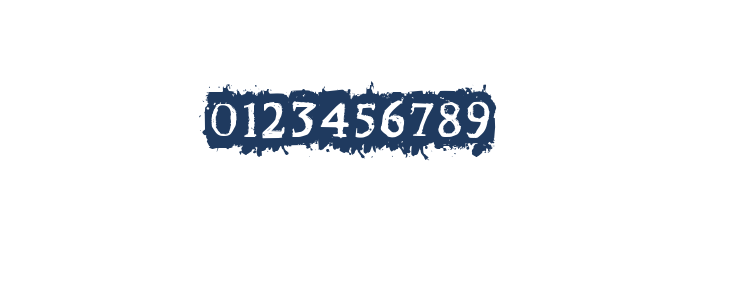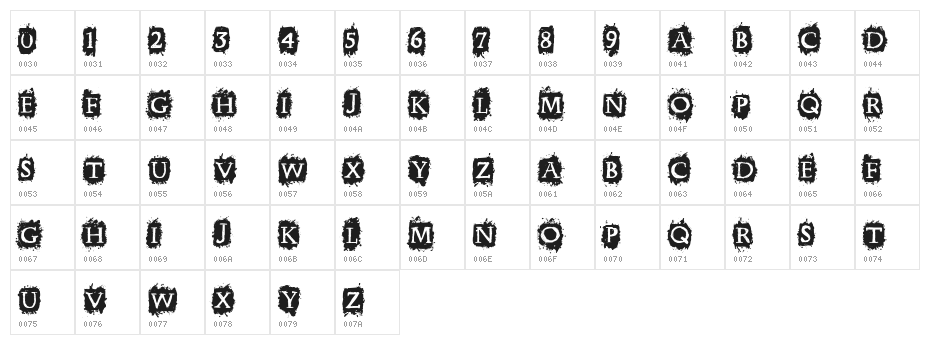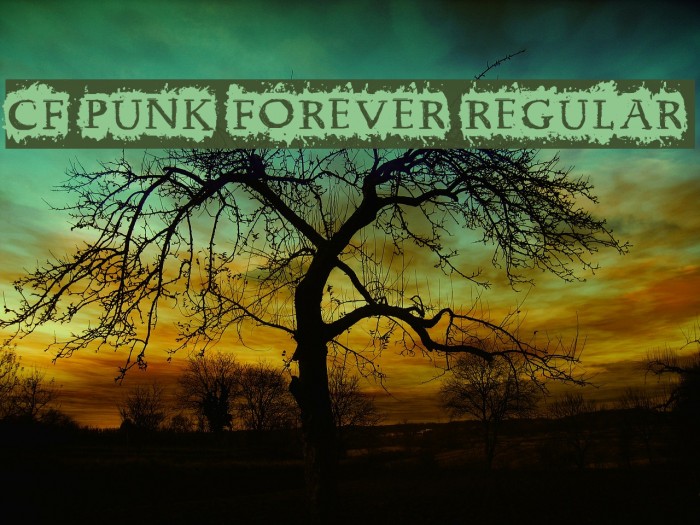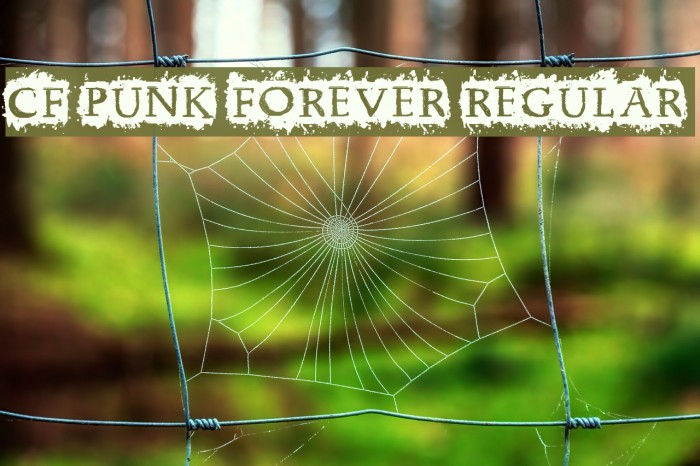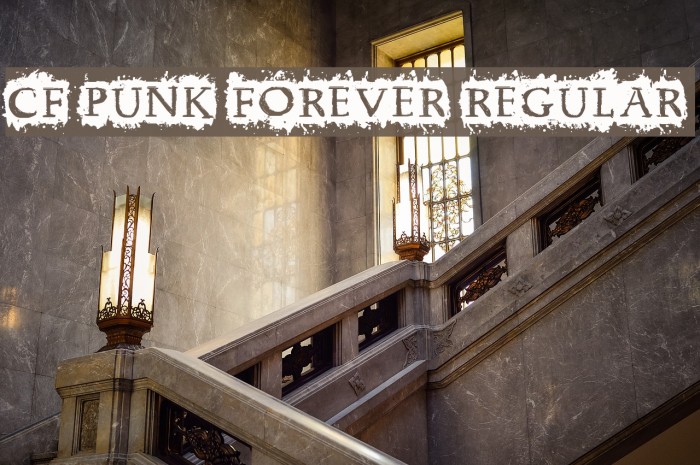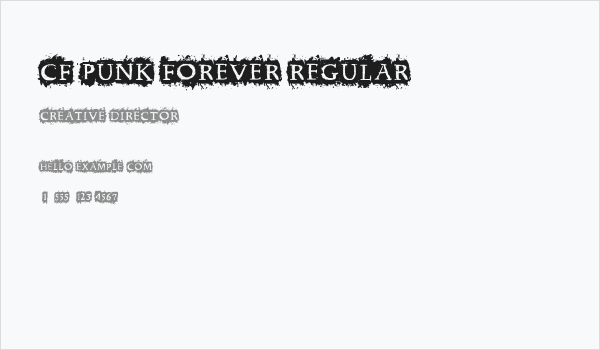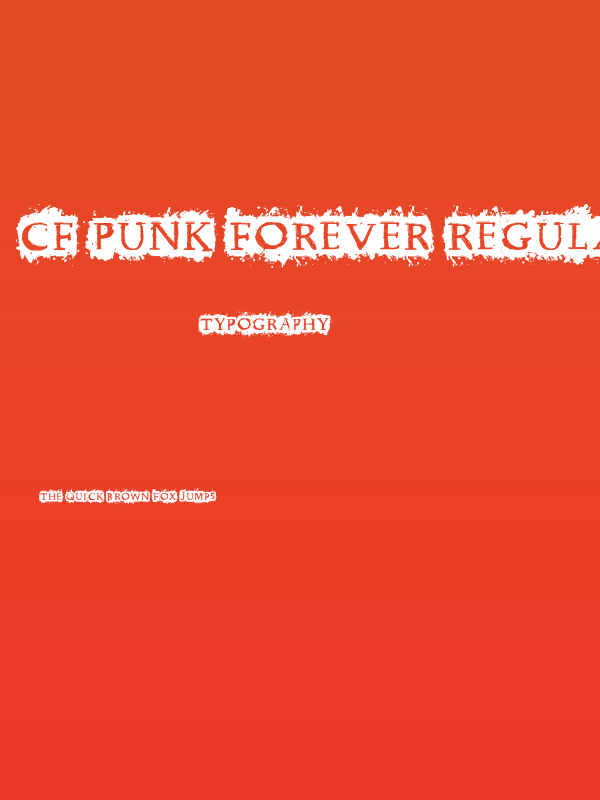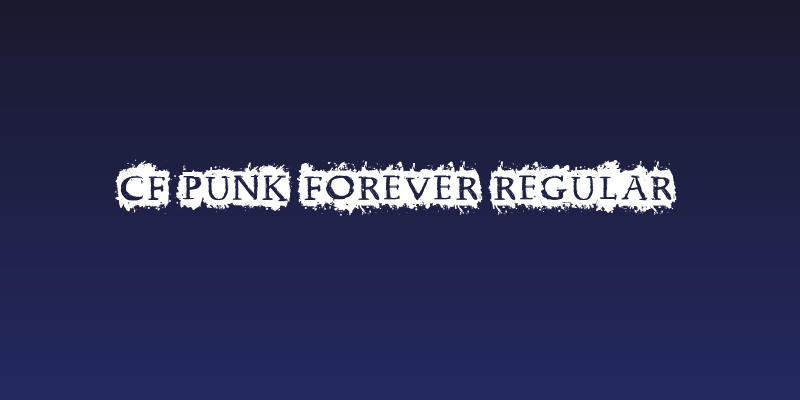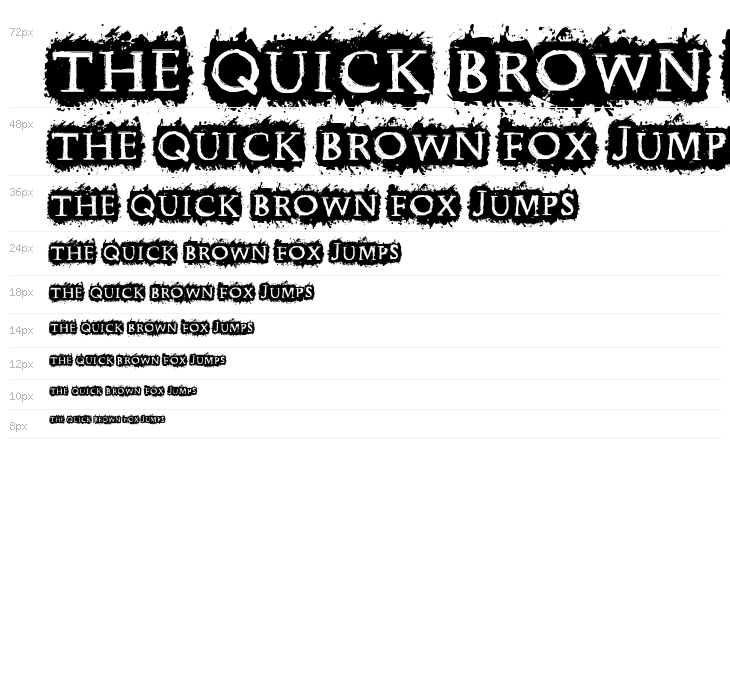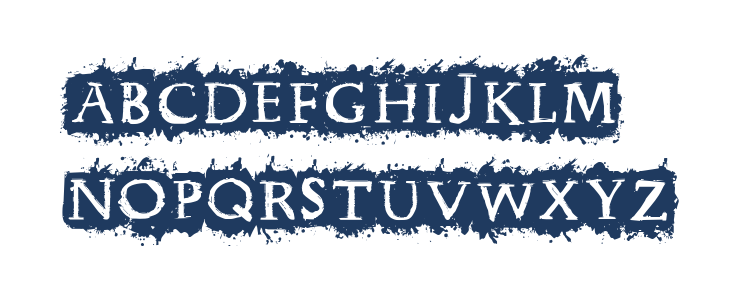
CF Punk Forever Regular Font
| Gesamtstil | Grunge, Rebellious |
| Anwendungsfall | Headlines, Posters, Album Covers |
| Vorgeschlagene Projekte | Ideal for music album covers, edgy posters, and creative projects needing a rebellious touch. |